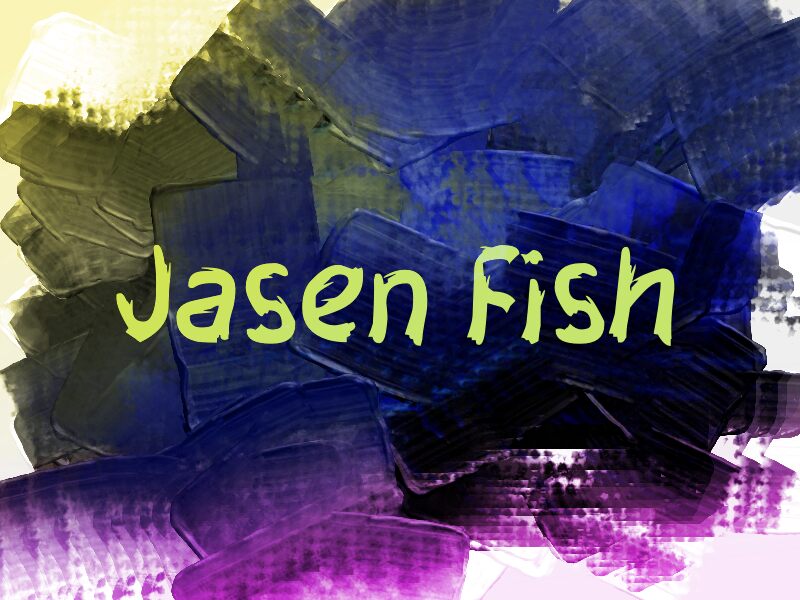
Jasen Fish от Wep — это бесплатный шрифт в стиле «треш-браш» с небрежным, живописным ритмом и дерзким характером уличных плакатов. Буквы словно нанесены щедро намоченной кистью: сочетание плотных округлых форм, рваных краев и резких срезов придает текстуре живую, неугомонную энергию, далекую от вылизанности.
Он идеально впишется в музыкальные флаеры, брендинг в стиле скейт и серф, обложки зинов, смелую упаковку и титры, где шрифт должен выглядеть быстро и осязаемо. Будучи бесплатным шрифтом, он также отлично подойдет для коротких заголовков, эскизов логотипов и эффектных постов в соцсетях, ведь грубые мазки кисти придают даже паре слов вид чего-то, что было расклеено по городу глубокой ночью.
Jasen Fish